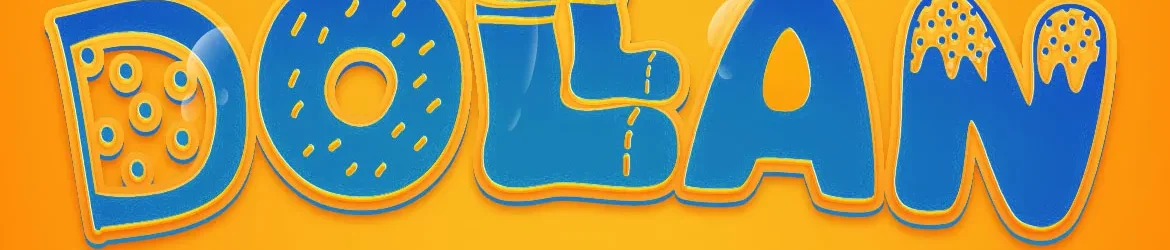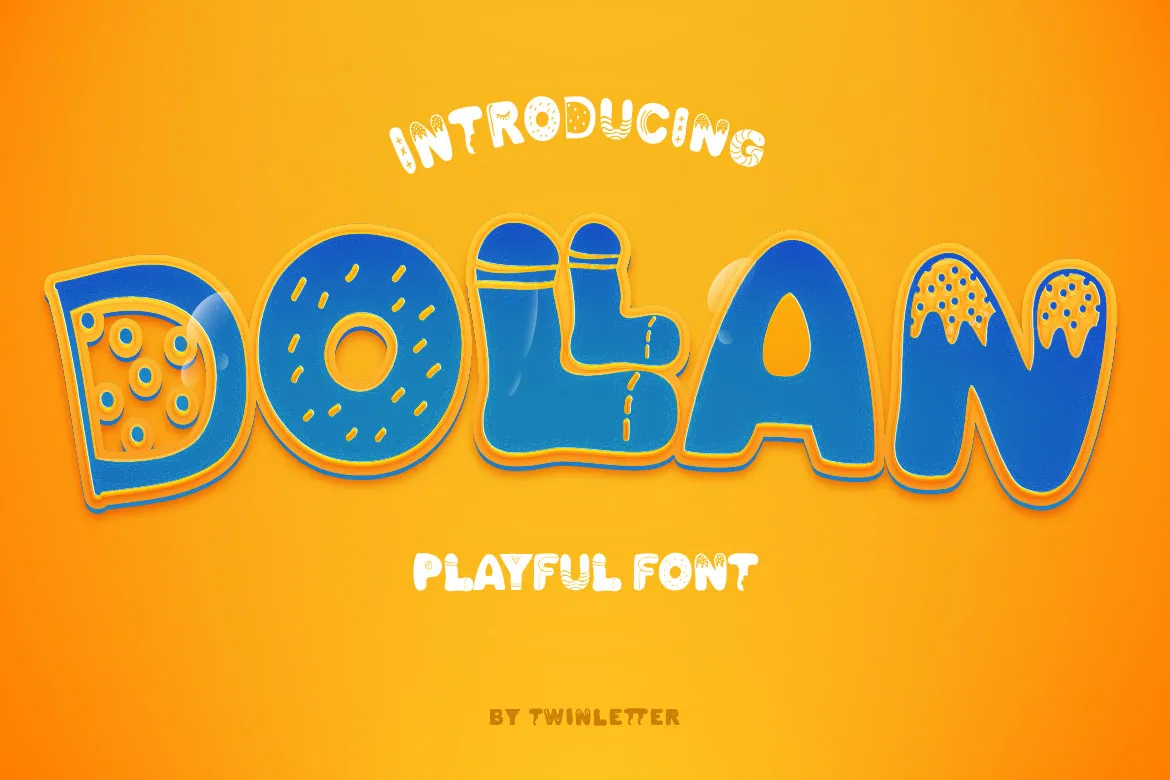
Dollan Font – Fonte Grátis
Dollan Font
Esta fonte Dollan é perfeita para projetos ambiciosos, pois oferece uma aparência única e chamativa que destacará sua individualidade. Trabalhada com um toque criativo e dinâmico, ela destaca a personalidade de cada letra. Com seu tom descontraído e vibrante, essa fonte traz uma identidade única aos trabalhos mais inovadores. Seja para criar slogans memoráveis ou montar logotipos intrigantes, Dollan estará sempre pronto para transformá-los em algo especial. Suavemente elegante e vigorosamente atemporal, esta é uma escolha perfeita para designers que valorizam originalidade e criatividade em suas criações visuais.